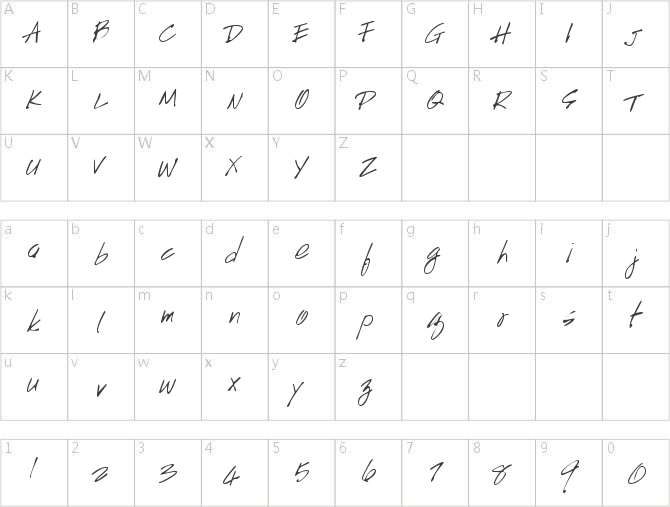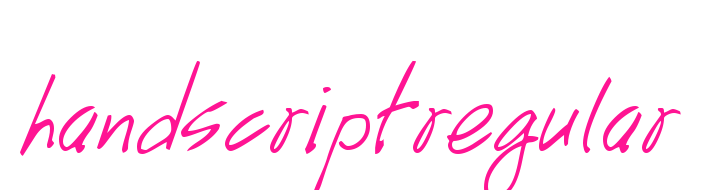
handscriptregular 詳情頁
handscriptregular
handscriptregular字體字庫是一款讓人賞心悅目、百看不厭的英文字體,適合各類廣告和產(chǎn)品包裝設(shè)計應(yīng)用,字體大小0.05MB,格式為ttf字體,上傳用戶是373790005,作者/版權(quán)方為未知